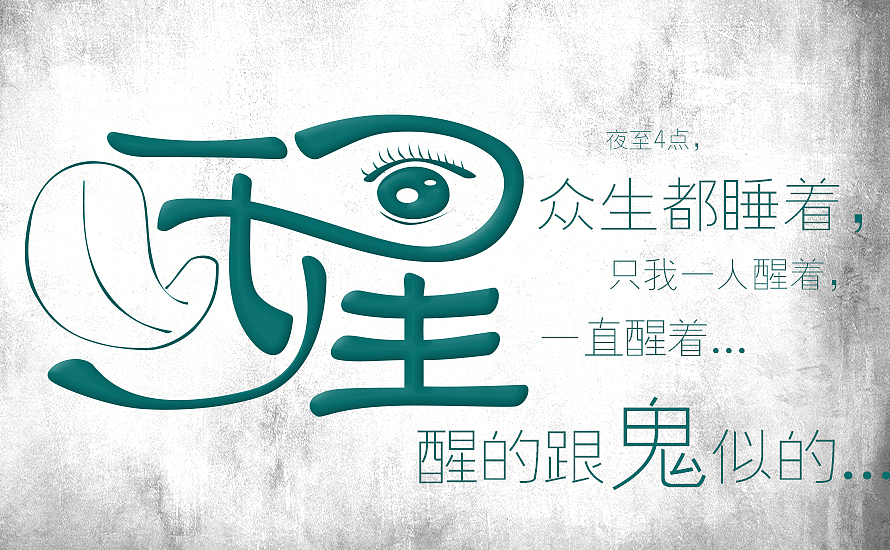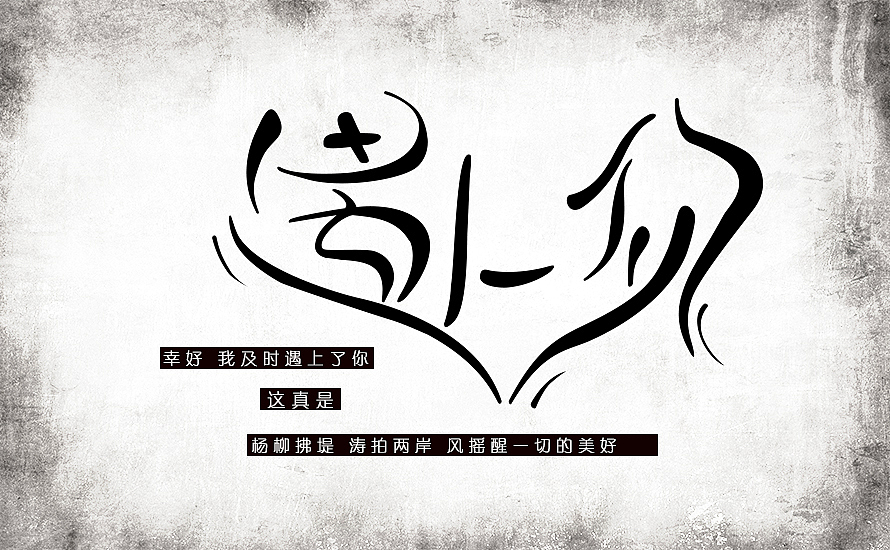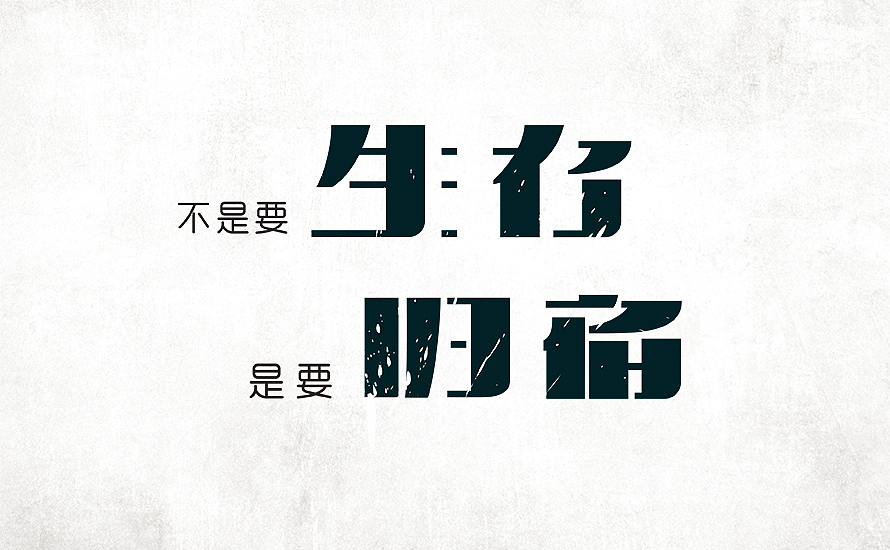
放肆与克制-原创字体设计第4辑
让我用字
跟你观一观世界
再谈一谈世界观
少谈些主义 多解决问题
前半生不好说 后半生说不好
创意是放肆 执行就是克制
翻看以前做的字 发觉现在的字慢慢有了“温度” 这是件值得高兴的事 我把她裱起来挂墙上 用来自勉
夜至四点 众生都睡着 只我一人醒着 一直醒着 醒的跟鬼似的
这是一个永远的诱饵 得不到 就这么牵着你往前走 信仰是一个让你自以为得到自由的东西
现在大把的时间 生活"宽敞"地反而让我不知所措 做字是我最舒适的填充方式
一个姑娘说 “就叫你邓先生吧” 我忆起木心的那一顶帽子
幸好 我及时遇上了你 这真是 杨柳拂堤 涛拍两岸 风摇醒一切的美好
生存与归宿